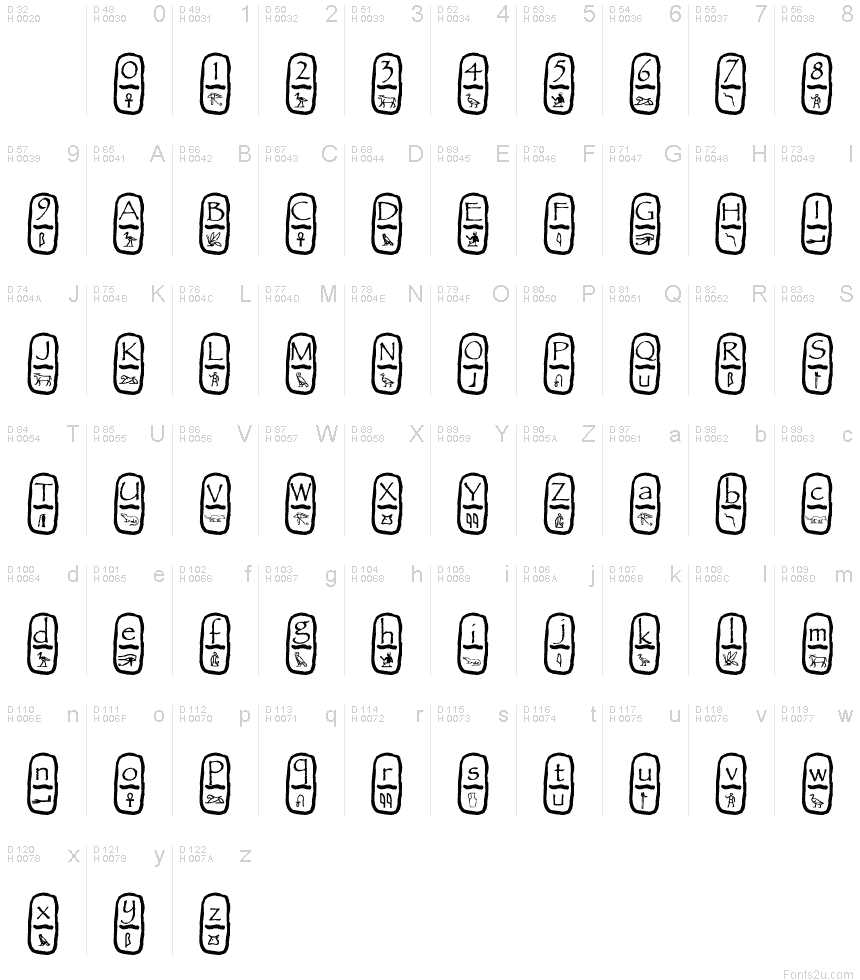
خط Cartouche من Pearlygates هو خط مجاني مزخرف للعناوين يحول كل حرف إلى خرطوش مصري مرسوم يدوياً. يستقر كل حرف داخل كبسولة غير منتظمة ذات مظهر حبري، مع حدود مهتزة وفراغات صغيرة تمنحك شعور النقوش الحجرية القديمة بدلاً من البكسلات الرقمية. تضفي ضربات الفرشاة الخشنة واللمسات الهيروغليفية الدقيقة على نصك طابعاً فورياً لجدران المقابر أو القطع الأثرية دون الحاجة إلى أي رسومات إضافية.
باستخدام Cartouche، يمكنك وضع علامة تجارية لغرف الهروب (escape rooms)، أو تصميم ملصقات للمعارض المتحفية، أو تزيين مواد دروس التاريخ، أو إنشاء دعوات ذات طابع خاص وخرائط كنوز تبدو وكأنها خرجت من تابوت مغبر. يعمل هذا الخط المجاني بشكل رائع أيضاً لأغلفة الكتب أو عناوين الألعاب في أنواع المغامرات والغموض. للحفاظ على سهولة القراءة، احتفظ بـ Cartouche بحجم كبير وقم بإقرانه بخط sans serif بسيط للنص الأساسي، لتبقى الخراطيش المصورة جريئة وواضحة.